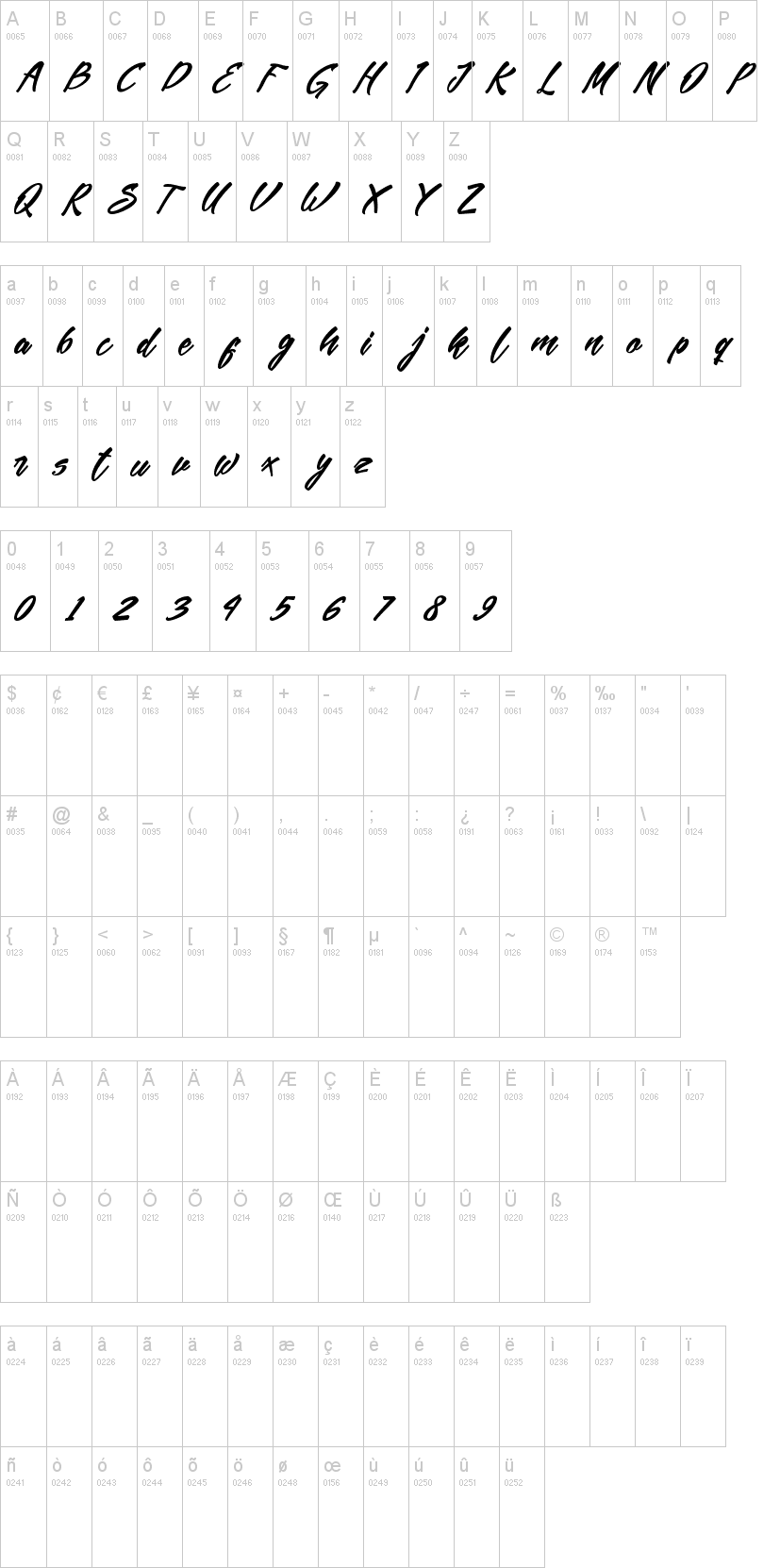
Mekar Script
Mekar Script 是一种手写风格的字体,具有艺术感和自然感。它的特点是细致的笔触和流畅的曲线,使得它看起来更加真实和有机。 Mekar Script 字体适用于各种场合,如设计,广告,海报,包装等。它提供了多种字重和风格,可以满足不同需求。此外,该字体也支持多种语言和字符集,包括西欧语言、中东语言和亚洲语言,可以用于国际化的设计项目。 总的来说,Mekar Script 字体是一种优美的手写字体,适用于多种设计场景,并且具有多语言支持,是一个非常实用的字体选择。
Mekar Script是一款非常不错的手写艺术字体,具有很好的视觉感,适合于文化类的宣传设计、商业类品牌的广告和产品包装设计以及个性化文字排版等较多场景。